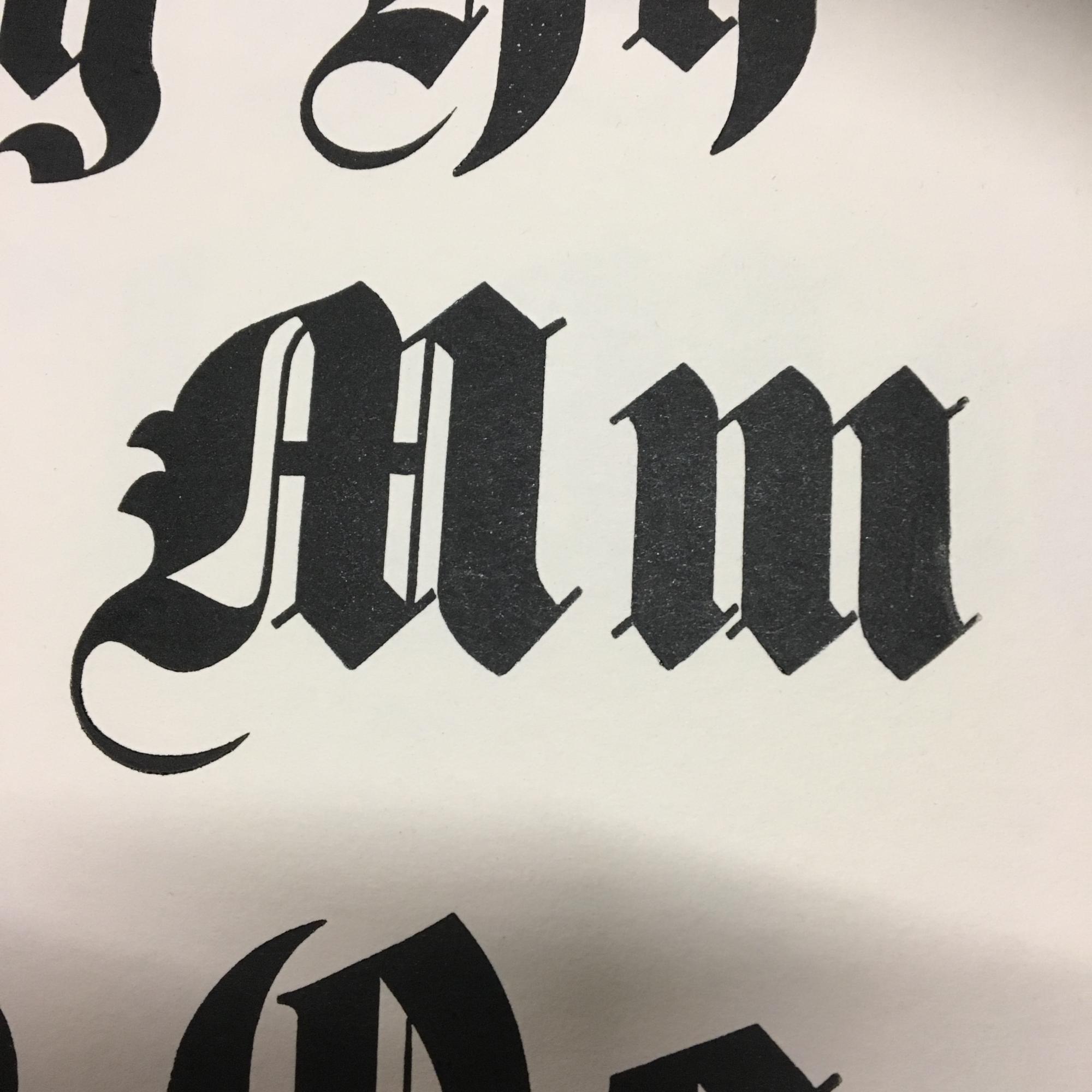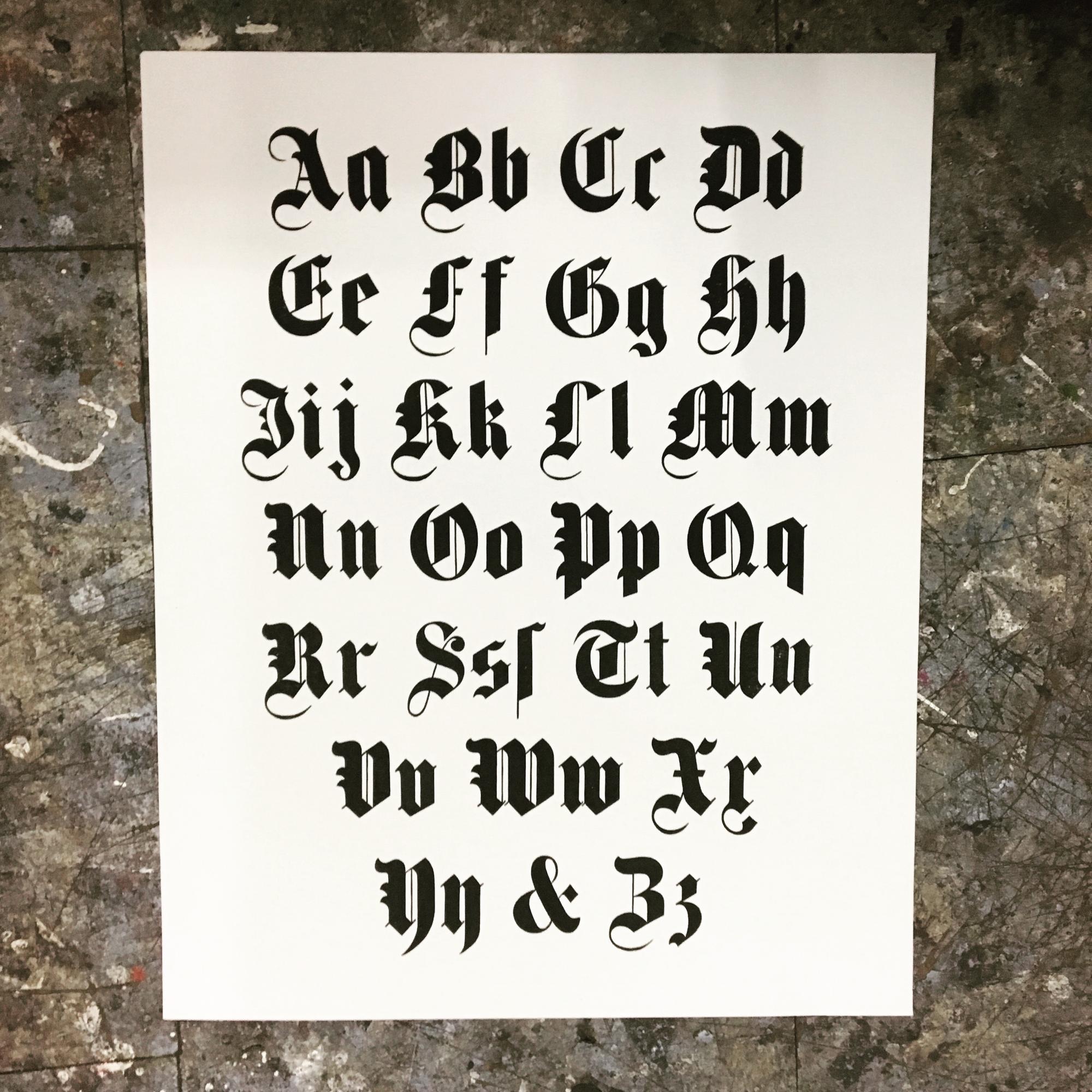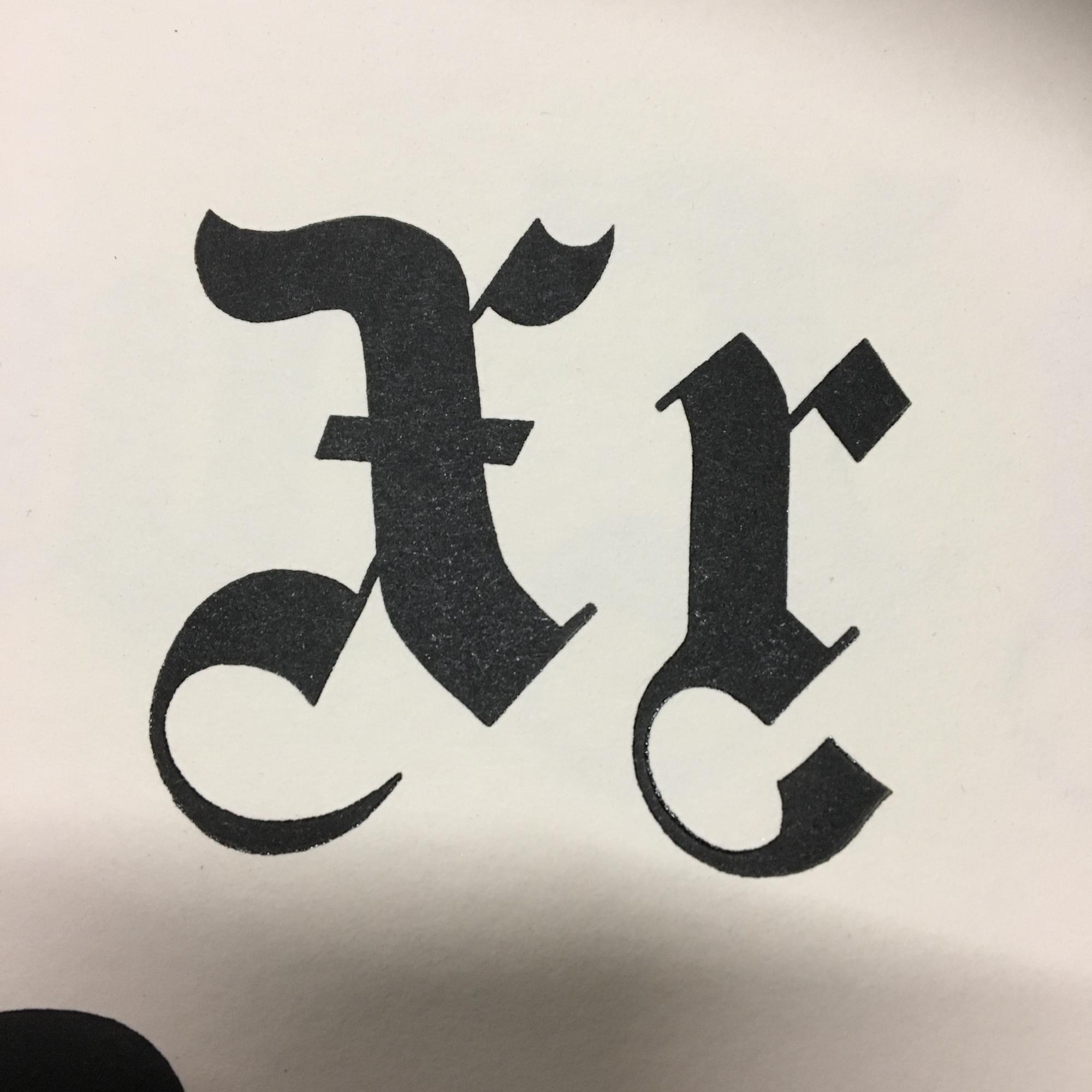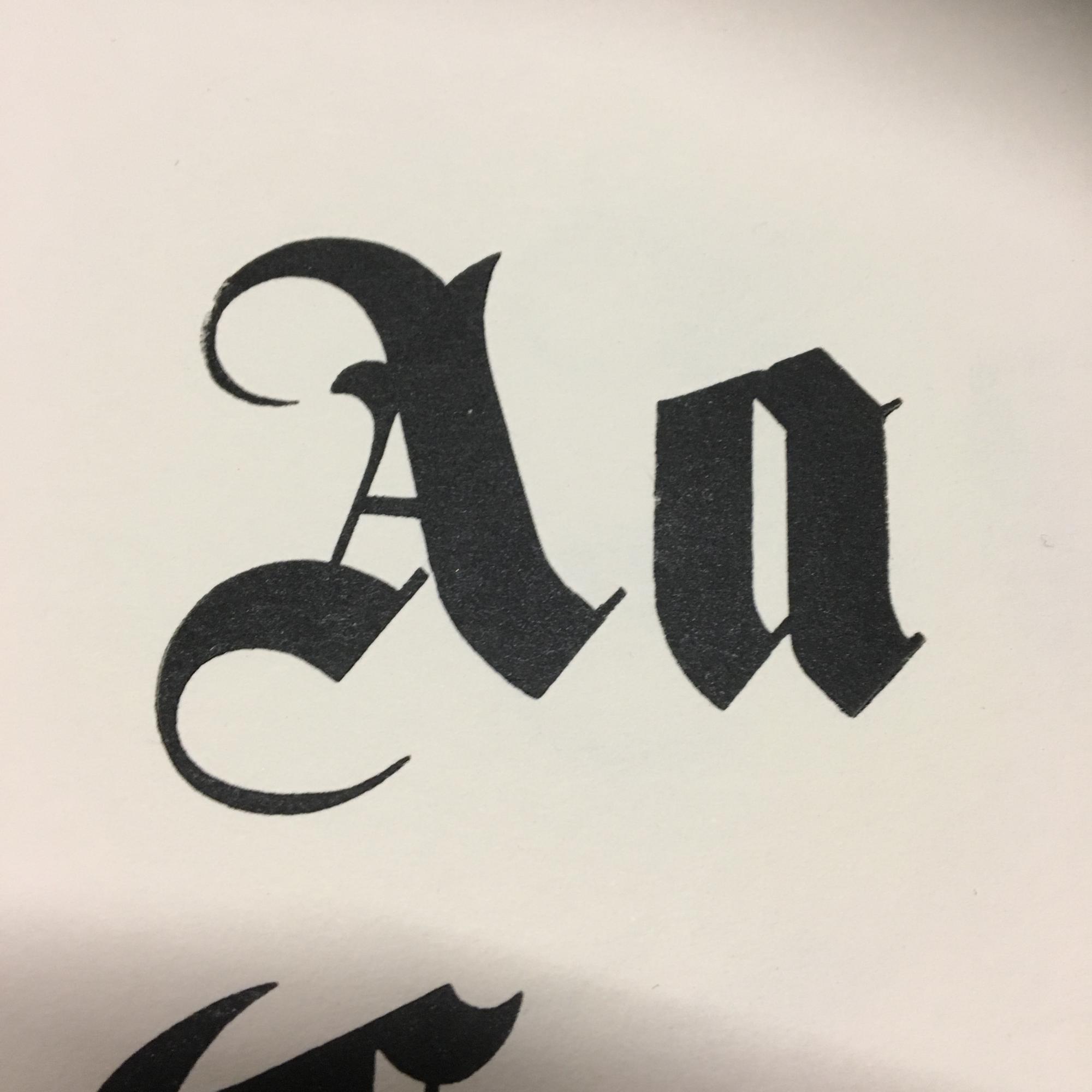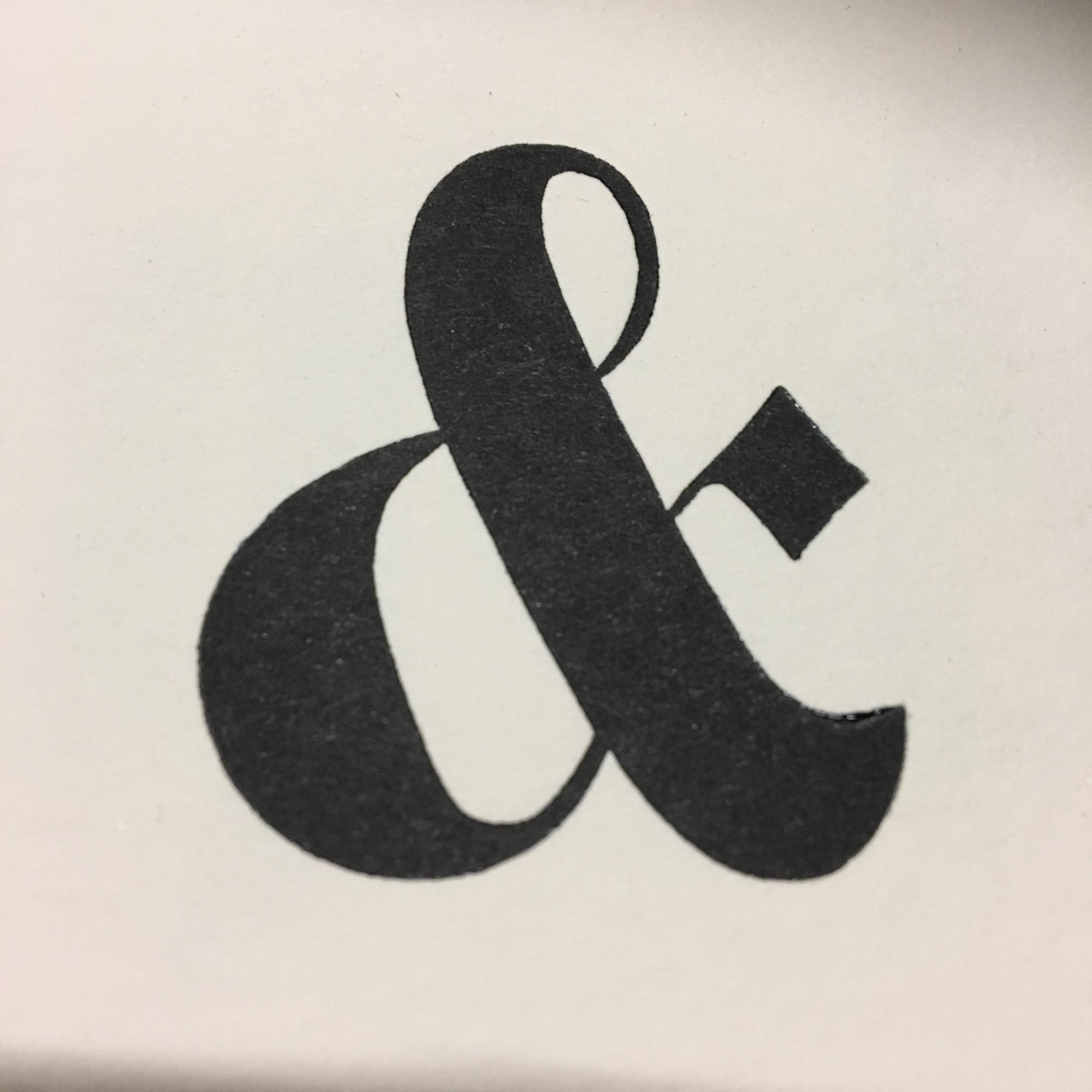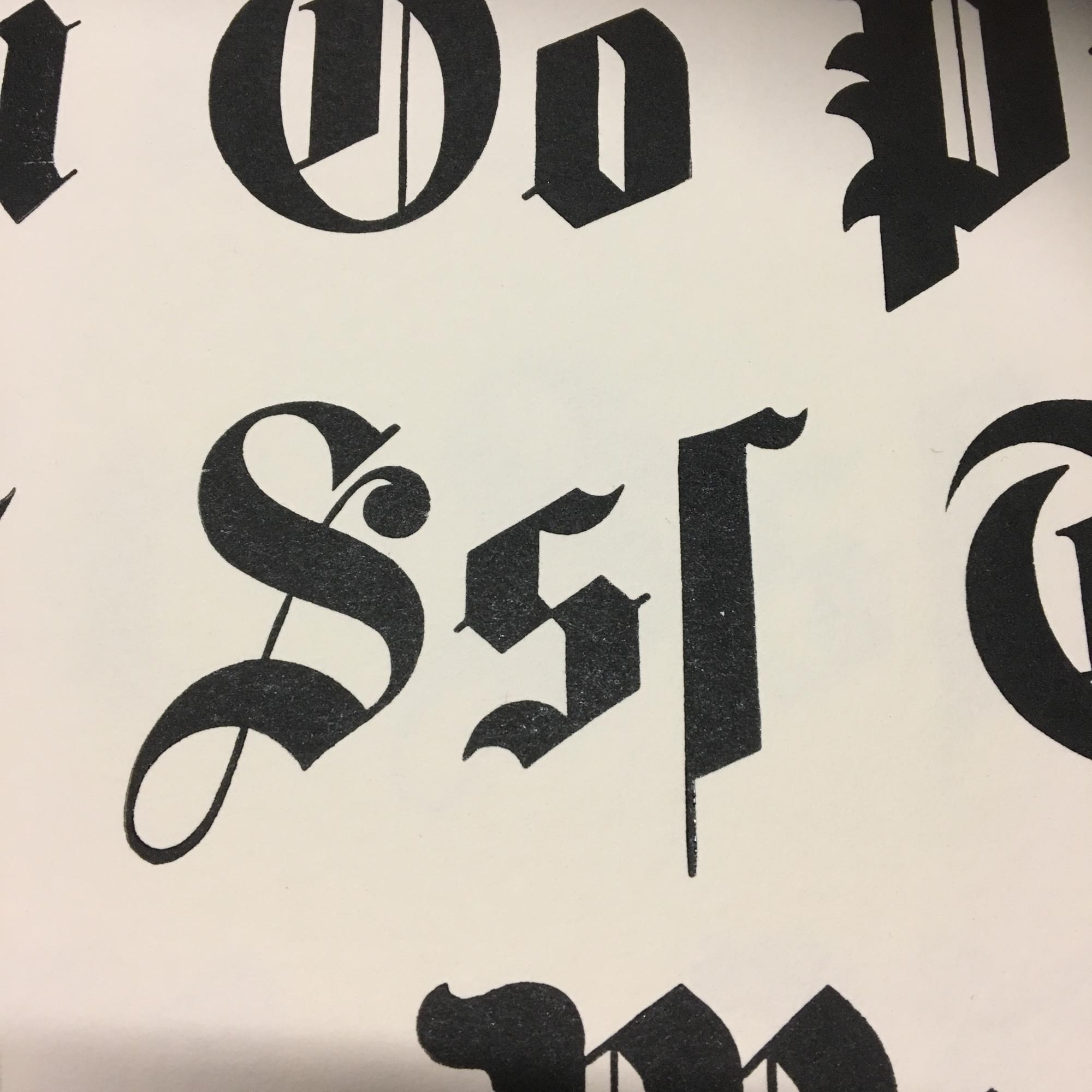
Alte Holzlettern-Fraktur, Schriftname gesucht.
ich habe vor kurzem folgende Holzlettern gekauft und würde gerne wissen, wie die Schrift heißt, damit ich mehr über sie herausfinden kann.
Anbei ein Andruck vom Alphabet, zwölf Cicero hoch.
das ist keine Fraktur. Das ist eine Textura, also eine Gotische. Siehe zuerst auf eine sehr ähnlich Schrift:
Typeface:	Fette Gotisch
Designer:	Friedrich Wilhelm Bauer
Year:		1875
Publisher:	Linotype
Die Stichworte für die Suche wären also Textura und/oder Gotisch. Ansonsten kannst Du Dir auch mal die ähnlichen Schriften unter den angegebenen Link ansehen. Vielleicht ist da eine noch nähere Schrift dabei?
Die Schrift dürfte nicht mehr im Originalzustand sein.
Einige Buchstaben wirken zumindest auf mich so, als würden sie nicht ganz dazupassen. Vielleicht sind sie im Laufe der Zeit verloren gegangen und dann dazugebastelt worden.
Z. B. passt das versal „S“ nicht zum Duktus der Schrift. Das „A“ hängt nach Links und das „L“ wirkt als würde es nach vorne kippen usw.
Generell weist die Schrift keine durchgängige Gestaltung auf.
Vielleicht wurde die Schrift auch nur der Originalschrift nachempfunden und in Holz gearbeitet.
Deshalb wird man auch m. E. keinen Namen der Schrift finden.
die gezeigte Schrift ist durchaus im Originalzustand, denn ich habe genau dieselbe, ebenfalls in 12 Cicero. Leider fehlen meinem Satz die Buchstaben A und B. Alle anderen Buchstaben sind jedoch gleich. Gerade habe ich noch einmal die Signaturen meines Satzes geprüft, sie sind durchweg identisch.
Dass derart alte Schriften keine durchgängige Gestaltung aufweisen ist mir gerade in letzter Zeit verstärkt aufgefallen. Wie der Kollege versuche auch ich derzeit diverse Holzletternsätze zu identifizieren.
Holzlettern wie auch Bleilettern hatten in der Zeit um 1850 vielfach keine Namen sondern einfach nur eine fortlaufende Nummer. Dies lässt sich in Katalogen aus der Zeit wie Teubner oder Heucke belegen.
Unter Umständen hatte die gezeigte Schrift daher nie einen Namen und wird namentlich nie gefunden werden.
Immerhin weiß ich damit, dass die Schrift schon recht alt ist.
@ Erwin Krump: das Hängen und die Schieflage liegen eher an meinen suboptimalen Kamerakünsten und dem dadurch verzogenem Bild.
Wenn es bei den "suboptimalen" Kamerakünsten nicht zu viel Arbeit macht, dürfte ich da vielleicht nach Fotos der Glyphen-Seite der Lettern selbst fragen - also mit dem Kegel, denn auch wenn die Schrift sich in der Gestaltung recht uneins zeigt, ist sie ja wohl schon so historisch, und ich würde gern eine digitalisierte Version davon machen. Lettern selbst geknipst würde dann auch die Vor- und Nachbreiten für mich vorgeben, und gleichzeitig eine Entzerrungs-Möglichkeit, wenn durch das Foto da was kippt?
für alle die es vielleicht interessiert anbei noch ein kleiner Schnappschuss der über das angedruckte Schriftmuster hinausgehenden Umlaute, Ligaturen und Ziffern.
Leider konnte ich das Bild nicht spiegeln.